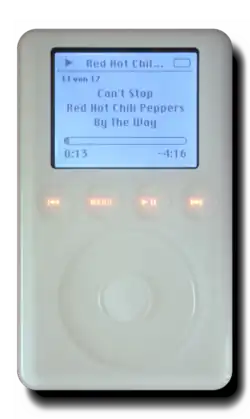
Chicago (Schriftart)
Chicago
Schriftart Chicago
Kategorie Sans-Serif
Schriftdesigner Susan Kare
Schriftgießerei Apple
Erstellung 1983
Beispiel
Schriftbeispiel für Chicago
Chicago ist eine serifenlose Schriftart, die von Susan Kare für Apple entwickelt wurde.[1] Sie war von 1984 bis 1997 die Systemschriftart der Macintosh-Betriebssysteme. Chicago fand ebenfalls in früheren Versionen der iPod-Oberfläche Verwendung.[2]
Ein iPod der dritten Generation mit der Chicago-Schriftart.